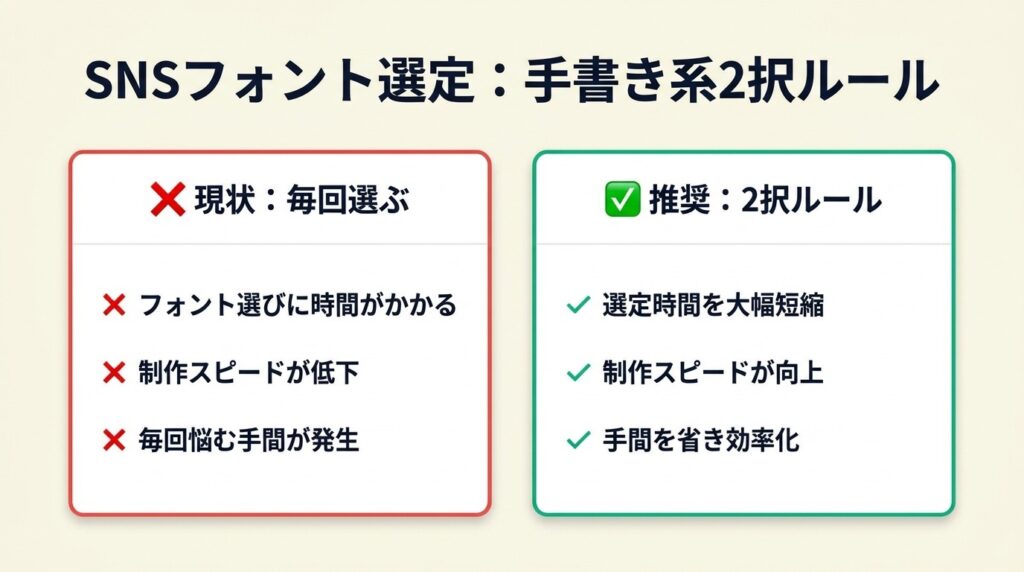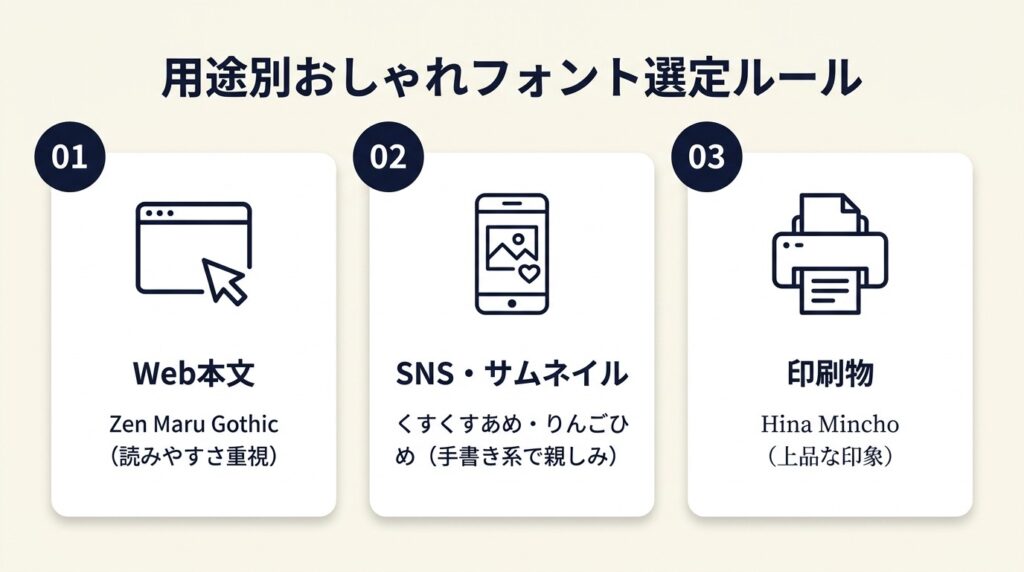
無料で使えるおしゃれな日本語フォントは2024年時点で多数存在し、商用利用可のものも多く公開されています。Google FontsやCanvaで即ダウンロードできるものを用途別に厳選し、選び方から適用手順まで解説します。
用途別(SNS・Web・印刷物)に最適なフォントを3分で特定できる
おしゃれな日本語フォントを探すなら、まずGoogle FontsとCanvaの無料フォントから始めるのが最速です。商用利用可・ひらがな漢字対応・Web埋め込み対応の3条件を満たすフォントに絞ると選択肢が大幅に絞られ、迷わず導入できます。用途別(手書き・丸ゴシック・明朝系)に1本ずつ選んで使い分けることで、プロらしい仕上がりになります。
おしゃれ日本語フォントは用途で3分類
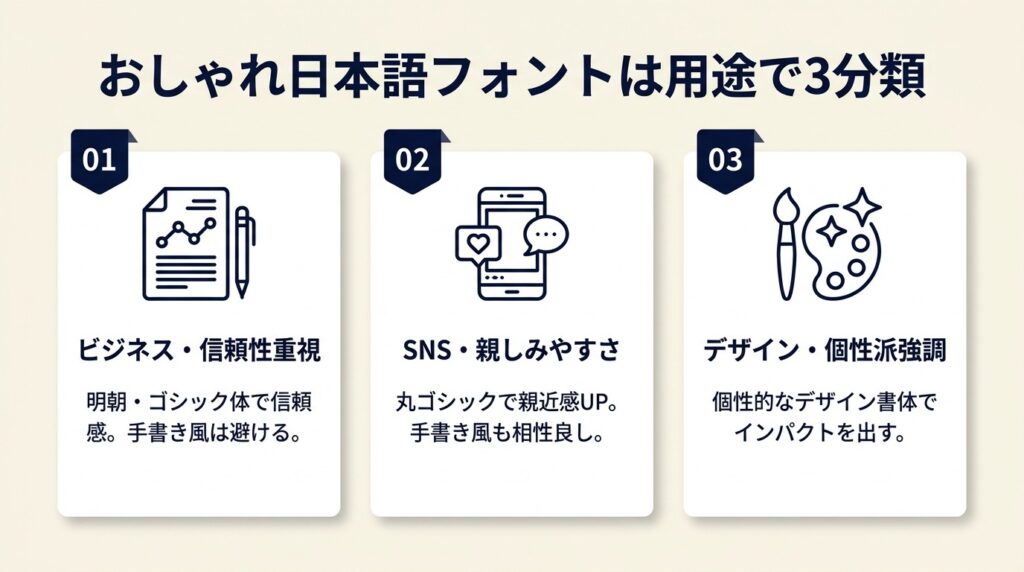
日本語フォントを「おしゃれ」と感じるかどうかは、用途との一致度で決まります。手書き風フォントをビジネス資料に使うと違和感が出る一方、丸ゴシックをInstagramのキャプションに使うと一気に親しみやすい印象になります。まず用途を決めてから選ぶと、迷いがゼロになります。
手書き風フォントはSNS・タイトルに特化
手書き風フォントの代表格として「くすくすあめ」と「りんごひめ(無料版)」がある。くすくすあめは丸みのある柔らかい筆致が特徴で、Instagramの投稿テキストやYouTubeサムネイルのタイトルに使うと、温かみのある印象を与える。りんごひめはレトロかわいい雰囲気を持ち、同人誌表紙やポップな告知バナーに向いている。いずれも商用利用可で、ffont.jpから無料ダウンロードできる。Instagram運用やYouTube編集を始めたばかりの方でも、ダウンロードから5分以内に実際の投稿へ適用できる。
丸ゴシック系はWebとブログ本文に最適
「Zen Maru Gothic」はGoogle Fontsで無料公開されているWebフォントで、シンプルさとカジュアルさを両立しています。文字の丸みが大きく、長文でも読み疲れしにくい設計です。WordPressやnoteなどのブログ本文に使うと、テキスト量が多いページでも圧迫感なく読み進められます。Webフォントとして使う場合はサーバー側への別途ファイル配置が不要で、HTMLの<head>タグに1行追加するだけで完結します。日本語フォント無料おすすめでは、Zen Maru Gothic以外にも業務で使える無料フォントを12種類以上まとめていますので、あわせて確認してみてください。
明朝系フォントは印刷物・縦書きに強い
「Hina Mincho」はGoogle Fontsで公開されている明朝系フォントで、丸みを取り入れた柔らかい印象が特徴です。横縦書き両対応でバランスが良く、A4の縦書きポスターや冊子の本文に適しています。Adobe Fontsのサブスク(月額2,728円〜)を利用すれば多数の高品質フォントも使えるようになり、出版物レベルの品質が求められる場面にも対応できます。
よくある質問
Q: 手書き風フォントは読みにくくなりますか?
A: 本文への使用は避け、タイトルや見出しに限定すると読みやすさを確保できます。本文には游ゴシックやZen Maru Gothicなど読みやすいフォントを組み合わせてください。
Q: 丸ゴシックと游ゴシックはどちらが読みやすいですか?
A: 長文WebテキストはZen Maru Gothic(丸ゴシック)、ビジネス文書・正式な資料は游ゴシックが適しています。目的の違いで選んでください。
おしゃれフォントの選び方を3分で診断
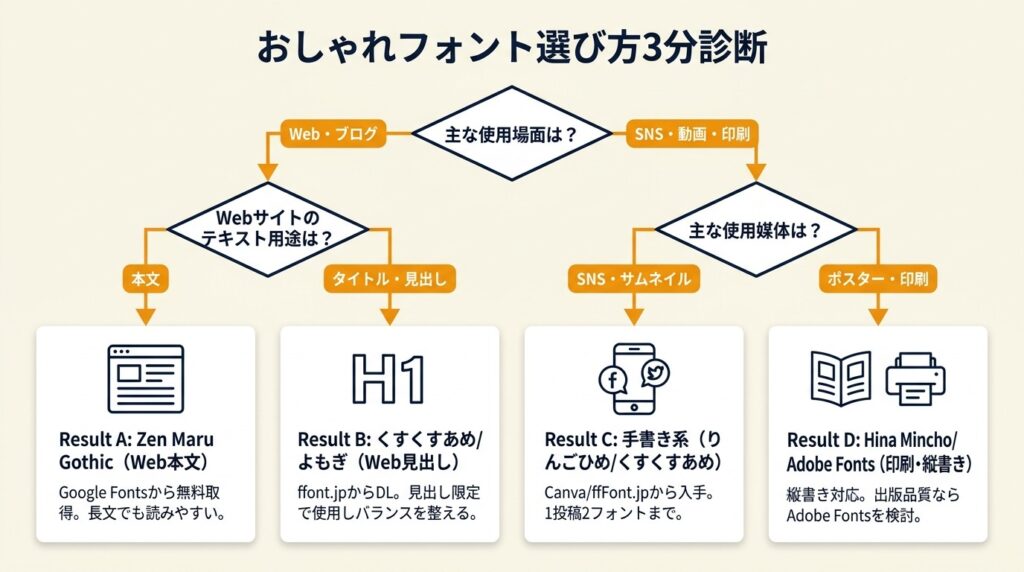
以下の質問に答えるだけで、今の用途に最適なフォントカテゴリが3分以内で判定できます。
Q1: 主な使用場面はどちらですか?
Webサイト・ブログ → Q2へ進んでください。
SNS・動画・印刷物 → Q3へ進んでください。
Q2: Webサイトのテキストとして使いますか?
主に本文(ボディテキスト)に使う →Result Aへ。
タイトル・見出しに使う →Result Bへ。
Q3: どの媒体が主な使用先ですか?
Instagram・X(Twitter)・サムネイル →Result Cへ。
ポスター・冊子・縦書き印刷物 →Result Dへ。
Result A: Zen Maru Gothic(Web本文)Google Fontsから無料取得し、CSSでfont-family: ‘Zen Maru Gothic’, sans-serif;を指定してください。長文でも読みやすく、ブログ・コーポレートサイト双方に対応します。
Result B: くすくすあめまたはよもぎフォント(Web見出し)ffont.jpからダウンロードし、H1・H2タグのみにフォント指定を限定します。本文と見出しでフォントを使い分けることで、全体のバランスが整います。
Result C: 手書き系(りんごひめ・くすくすあめ)CanvaまたはffFont.jpから入手し、テキストボックスのフォント設定から選択します。1投稿あたり最大2種類のフォントに絞るとデザインの統一感が出ます。
Result D: Hina MinchoまたはAdobe Fonts(印刷・縦書き)**Google Fontsで無料公開のHina Minchoは縦書き印刷に対応しています。出版品質が必要な場合はAdobe Fontsの高品質フォントを検討してください。
よくある質問
Q: 複数のResultに当てはまる場合はどうすればいいですか?
A: 最も頻度の高い用途のResultを優先し、1本のフォントを決めてください。フォントの数を増やすより、1本を深く使いこなす方が短期間でデザインの質が上がります。
Q: 診断結果のフォント以外を使っても問題ありませんか?
A: 問題ありません。ためしがき(tameshigaki.jp)でテキストを入力してプレビューを確認し、実際の見た目で最終判断するのが最も確実です。
おしゃれ日本語フォントは5つの仕組みで使いこなす
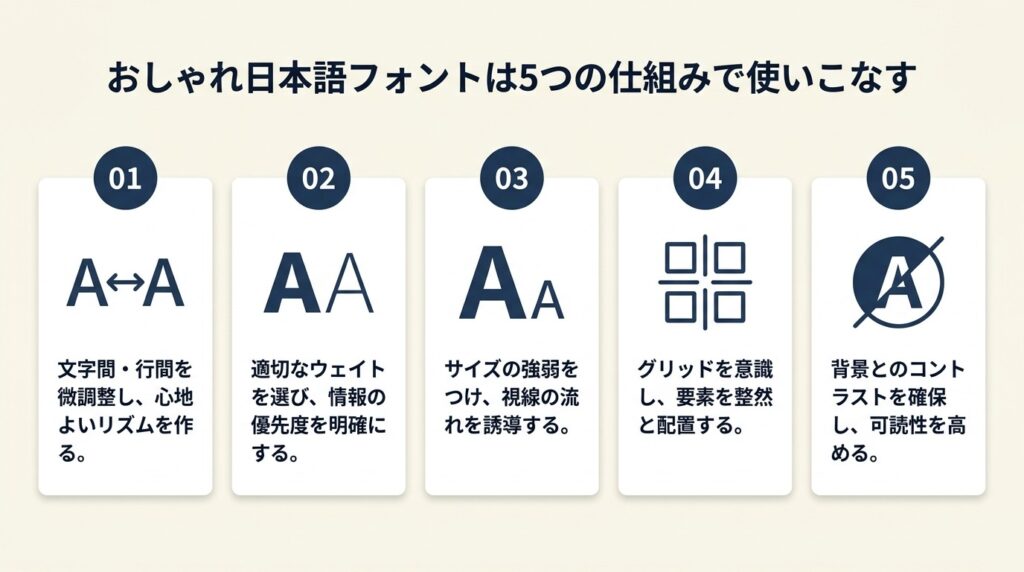
フォント名をそのままダウンロードするだけでは、プロらしい仕上がりになりません。フォントの使い方そのものに差が出るポイントを5つ押さえることで、同じフォントを使っていても仕上がりに明確な差が生まれます。
ハック1: Zen Maru GothicのCSS1行でWebを即おしゃれに
【対象】: WordPressやHTML/CSSを編集できるWebサイト運営者
【手順】:
ステップ1(2分): Google Fontsで「Zen Maru Gothic」を検索し、「Get font」→「Get embed code」からHTMLコードをコピーする。
ステップ2(3分): WordPressのテーマエディターまたはHTMLの<head>タグ内にコピーしたlinkタグを貼り付ける。
おしゃれ フォント 日本語に関するよくある質問